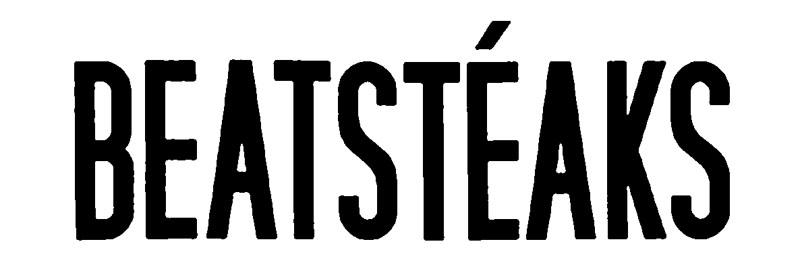
Schrift von Beatsteaks T-Shirt
hier mal weitere ähnliche Schriften:
Typeface: Filmotype Giant
Designers: Patrick Griffin and Rebecca Alaccari
Year: 2011
Publisher: Filmotype
Hier gibt es die OPTI Gigant zum freien Download, aber die Lizenzfrage ist da etwas ungeklärt:
Auch nahe dran ist die Steelfish von Ray Larabie:
Dann hätte ich da noch die Gobold (AllCaps) von 7NTypes
»Hopfen« von Martin Borst (Seiten 4 & 15)
Typeface: Block Gothic Extra Condensed
Designer: Steve Jackaman
Year: 1994
Publisher: Red Rooster Collection
Based on the Block Gothic series circa 1960.